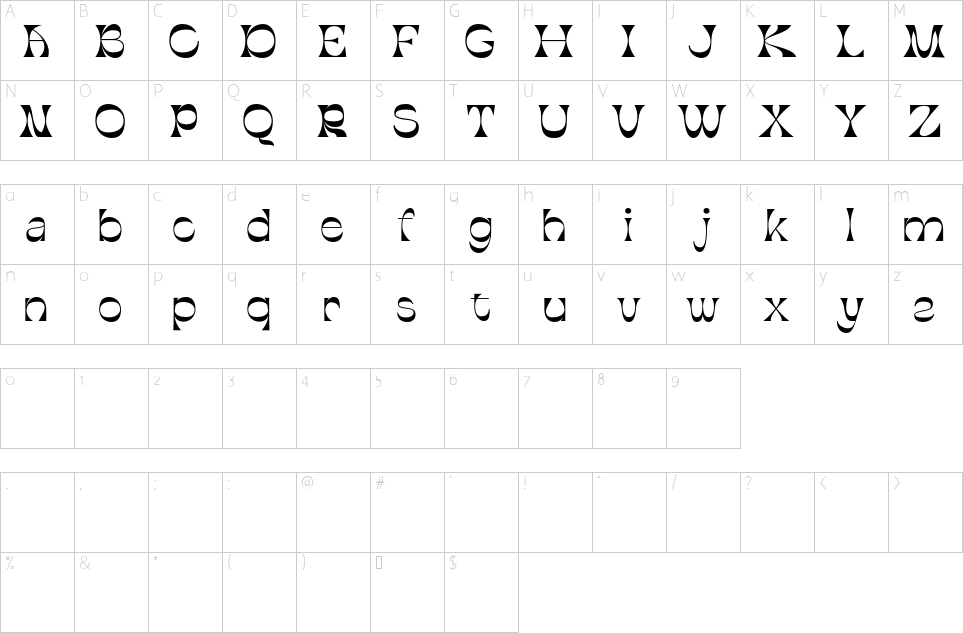
Abeleo é uma fonte gráfica elegante e envolvente, perfeita para designers que procuram um visual agradável para seus projetos. Desenvolvida pela Craft Supply Co, esta fonte apresenta linhas fluidas e detalhes sutis que a tornam um recurso valioso para o seu trabalho. Com um design cuidadosamente elaborado, Abeleo oferece um estilo contemporâneo que se destaca em qualquer projeto. Para quem está buscando fontes gratuitas para Windows e Mac, Abeleo é uma opção confiável. Desenvolvida para os designers que querem uma escolha de fontes limpa e sofisticada, Abeleo é um recurso valioso para qualquer estilista. Com seu download fácil e versátil, Abeleo é a escolha certa para quem busca uma fonte de qualidade gratuita.